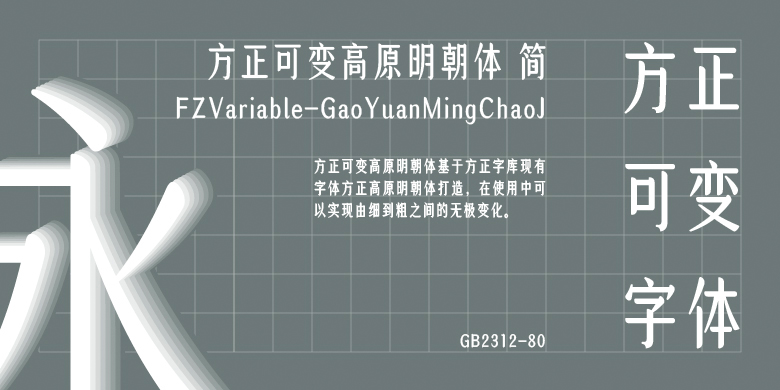
方正可變高原明朝體 簡
方正可變高原明朝體支持文字粗細無級調節,設計師通過調整字重軸(Weight)的變化,可以實現字形的平滑連續的細微調整,滿足不同版式的設計需求。 方正高原明朝體是一款以作者母親名字命名的字體,字形基于宋體經典且優雅的結構設計而成,減少了宋體具有相對鋒芒修飾感的字腳,筆畫圓潤工整,韻律節奏恰如其分,構建出一款字形修?、勻稱、雅韻,極具干練?華之氣質美感的家族字體。 此款字體適合時尚、醫美、化妝品類行業廣告用字及畫報雜志標題。